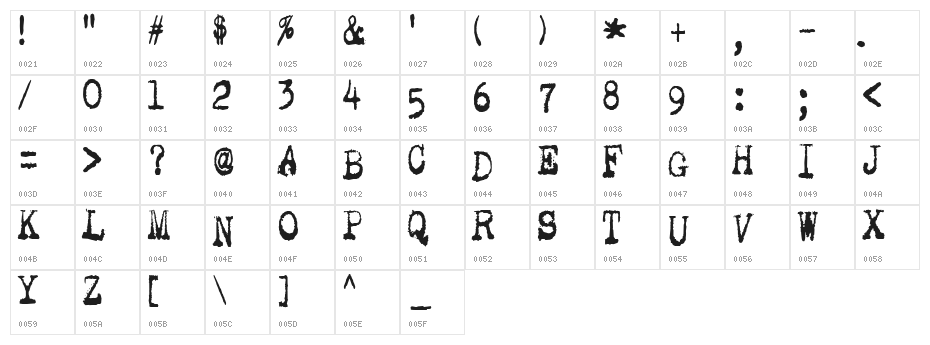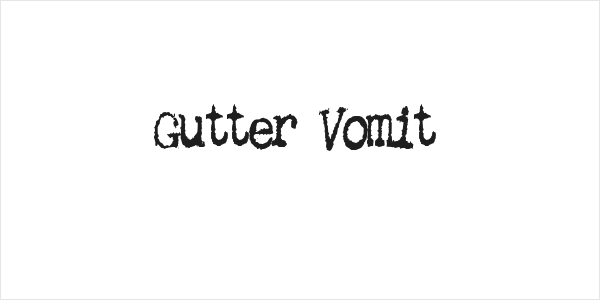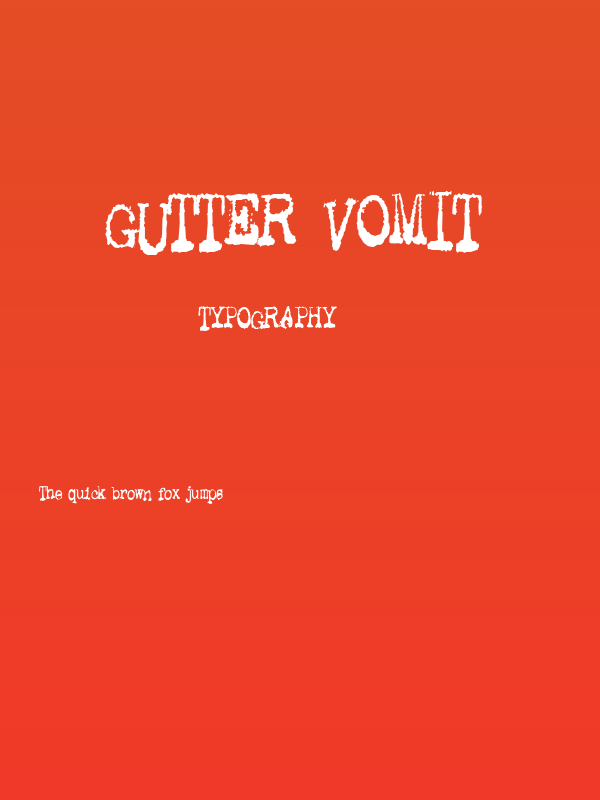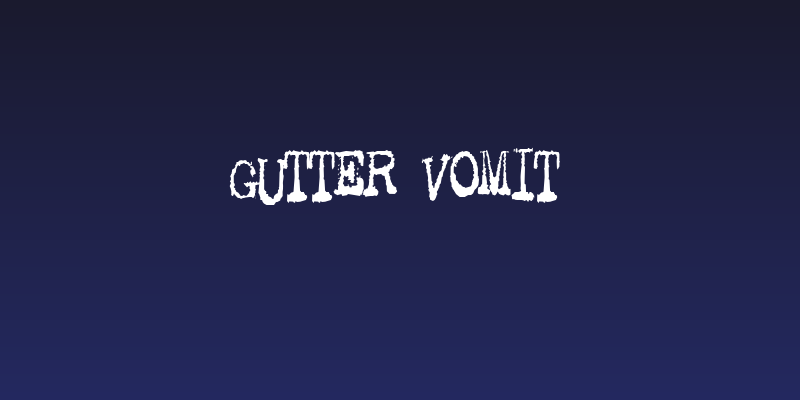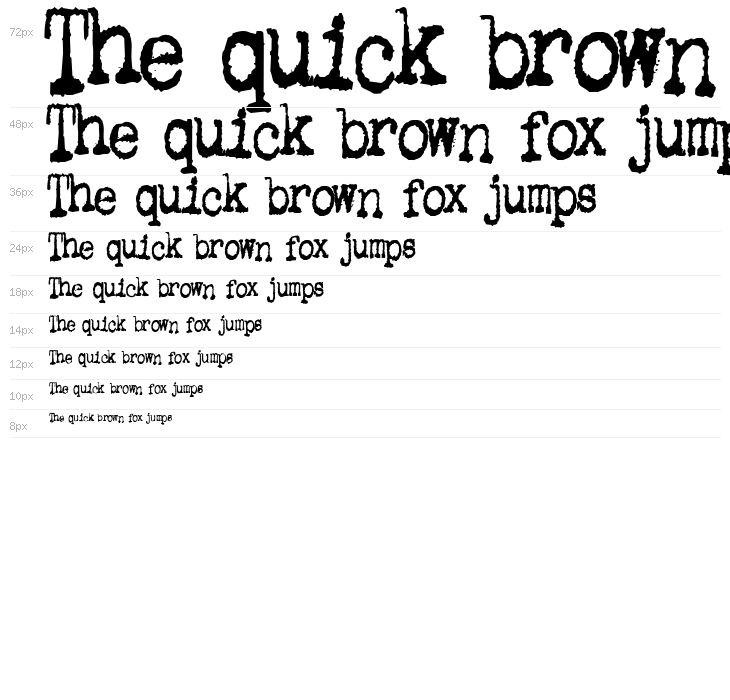
Gutter Vomit Font
| Stile generale | Grunge, Urban, Edgy |
| Caso d'uso | Logos, Posters, Album Covers |
| Progetti proposti | Ideal for music album covers, streetwear branding, alternative event posters, and any project needing an edgy, urban aesthetic. |